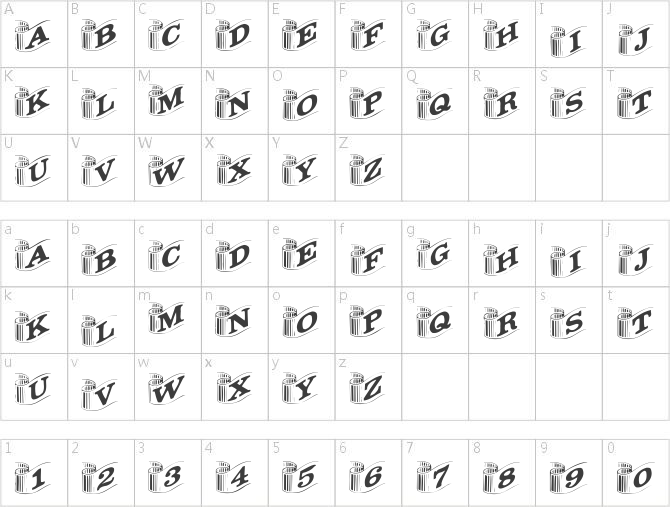
FZ BORDERS 7 EX 詳情頁(yè)
FZ BORDERS 7 EX字體字庫(kù)是一款讓人賞心悅目、百看不厭的英文字體,適合各類(lèi)廣告和產(chǎn)品包裝設(shè)計(jì)應(yīng)用,字體大小0.16MB,格式為ttf字體,上傳用戶是Me / ,yD ,作者/版權(quán)方為未知